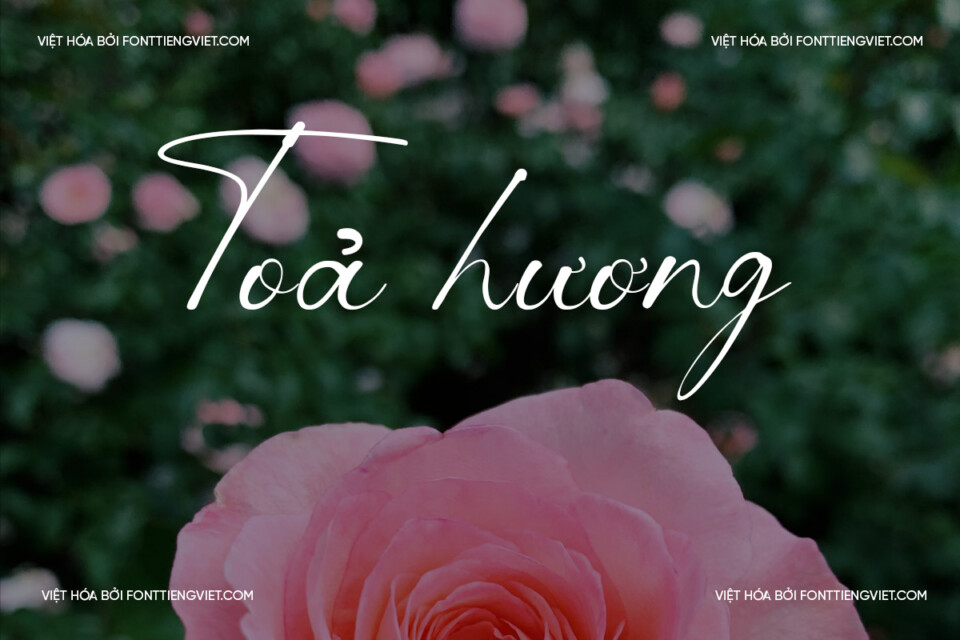
Trong thế giới thiết kế đồ họa đầy màu sắc và sáng tạo, việc lựa chọn một Font Chữ phù hợp có thể tạo nên sự khác biệt đáng kể cho bất kỳ dự án nào. Đặc biệt, với những ai đang tìm kiếm sự tinh tế, mềm mại và một chút cá tính nghệ thuật, Font Việt hóa 1FTV VIP Lorenna Script nổi lên như một lựa chọn không thể bỏ qua. Đây không chỉ là một font chữ đơn thuần, mà còn là một công cụ mạnh mẽ giúp truyền tải cảm xúc và câu chuyện thông qua từng nét chữ. Từ những thiệp mời sang trọng, poster quảng cáo độc đáo cho đến các ấn phẩm cá nhân, Lorenna Script Việt hóa mang đến một vẻ đẹp vượt thời gian, kết hợp hài hòa giữa nét cổ điển và hiện đại, chắc chắn sẽ làm hài lòng cả những nhà thiết kế khó tính nhất. Bài viết này sẽ đi sâu khám phá những đặc điểm nổi bật và lý do tại sao font chữ này lại được ưa chuộng đến vậy.
Sức Mạnh Của Font Việt hóa 1FTV VIP Lorenna Script Trong Mọi Thiết Kế
Font Việt hóa 1FTV VIP Lorenna Script không chỉ đơn thuần là một kiểu chữ đẹp mà còn là một biểu tượng của sự sang trọng và tinh tế. Với thiết kế lấy cảm hứng từ những nét chữ viết tay mềm mại, uyển chuyển, font này mang đến một cảm giác rất “thật” và cá nhân hóa. Mỗi ký tự đều được chăm chút tỉ mỉ, từ độ cong của nét chữ đến khoảng cách giữa các chữ cái, tất cả đều tạo nên một tổng thể hài hòa và dễ đọc. Điều này đặc biệt quan trọng trong các dự án đòi hỏi sự chú ý đến từng chi tiết nhỏ, như thiết kế logo, bao bì sản phẩm hay các ấn phẩm cao cấp. Khả năng tương thích tốt với nhiều ngôn ngữ, đặc biệt là tiếng Việt với các ký tự dấu chuẩn xác, là một điểm cộng lớn, giúp các nhà thiết kế Việt Nam có thể tự tin sử dụng mà không lo lắng về lỗi hiển thị. Lorenna Script Việt hóa không chỉ là một font, đó là một phong cách.
Điểm mạnh thực sự của Lorenna Script nằm ở tính linh hoạt của nó. Dù bạn đang thiết kế một tấm thiệp cưới lãng mạn, một banner quảng cáo sáng tạo hay thậm chí là một bìa sách nghệ thuật, font chữ này đều có thể phát huy tối đa vẻ đẹp của mình. Sự mềm mại nhưng không kém phần mạnh mẽ của nó giúp tạo ra một điểm nhấn thị giác ấn tượng, thu hút ánh nhìn của người xem ngay từ cái nhìn đầu tiên. Đối với các dự án yêu cầu sự độc đáo và khác biệt, việc sử dụng Lorenna Script Việt hóa sẽ giúp sản phẩm của bạn nổi bật hơn hẳn so với những thiết kế thông thường. Đây là một lựa chọn tuyệt vời để thể hiện sự chuyên nghiệp và gu thẩm mỹ tinh tế của người thiết kế.
Ưu Điểm Nổi Bật Của Font Script Việt Hóa
Khi nói đến font chữ script, khả năng Việt hóa là một yếu tố then chốt, và Font Việt hóa 1FTV VIP Lorenna Script đã làm rất tốt điều này. Việc sở hữu một bộ font được Việt hóa đầy đủ không chỉ đảm bảo rằng các ký tự có dấu của tiếng Việt sẽ hiển thị một cách chính xác và đẹp mắt, mà còn giúp duy trì tính thẩm mỹ tổng thể của thiết kế. Không còn những lỗi hiển thị khó chịu hay sự không nhất quán về kiểu dáng giữa các ký tự có dấu và không dấu. Điều này giúp tiết kiệm đáng kể thời gian chỉnh sửa và đảm bảo chất lượng cao nhất cho sản phẩm cuối cùng. Một font script được Việt hóa tốt như Lorenna Script là minh chứng cho sự quan tâm đến người dùng Việt, mang lại trải nghiệm sử dụng trọn vẹn và hiệu quả.
Bên cạnh đó, phong cách viết tay của Lorenna Script còn giúp tạo ra một cảm giác thân thiện và gần gũi. Trong bối cảnh truyền thông ngày càng trở nên cá nhân hóa, việc sử dụng các yếu tố mang tính thủ công, nghệ thuật như font script này sẽ giúp thương hiệu hoặc thông điệp của bạn dễ dàng kết nối với đối tượng mục tiêu hơn. Nó gợi lên sự ấm áp, chân thành và một chút hoài niệm, rất phù hợp cho các ngành nghề như làm bánh, thủ công mỹ nghệ, nhiếp ảnh, hoặc các sự kiện đặc biệt. Sự đa dạng trong ứng dụng làm cho font chữ này trở thành một tài sản quý giá trong bộ sưu tập của bất kỳ nhà thiết kế nào muốn tạo ra những tác phẩm có hồn và ý nghĩa.
Cách Tối Ưu Sử Dụng Lorenna Script Cho Dự Án Của Bạn
Để tối ưu hóa việc sử dụng Font Việt hóa 1FTV VIP Lorenna Script, có một vài mẹo nhỏ mà bạn có thể áp dụng. Đầu tiên, hãy sử dụng font này cho các tiêu đề, slogan, hoặc những đoạn văn bản ngắn cần tạo điểm nhấn mạnh mẽ. Do tính chất là một font script, việc dùng nó cho toàn bộ các đoạn văn bản dài có thể gây khó đọc. Thay vào đó, hãy kết hợp Lorenna Script với một font sans-serif hoặc serif đơn giản, dễ đọc cho phần nội dung chính. Sự tương phản giữa hai loại font sẽ tạo nên một bố cục cân bằng và chuyên nghiệp. Ví dụ, bạn có thể dùng Lorenna Script cho tên thương hiệu hoặc tiêu đề của thiệp mời, và dùng một font chữ cơ bản hơn cho các chi tiết thông tin.
Thứ hai, hãy chú ý đến màu sắc và kích thước. Lorenna Script sẽ tỏa sáng nhất khi được đặt trong một không gian đủ thoáng và có màu sắc tương phản tốt với nền. Đừng ngại thử nghiệm với các kích thước khác nhau để xem font chữ này thể hiện tốt nhất ở đâu. Đôi khi, một chút biến tấu về màu sắc hoặc hiệu ứng đổ bóng cũng có thể làm tăng thêm vẻ đẹp và sự độc đáo của font. Cuối cùng, luôn luôn kiểm tra tổng thể thiết kế trên các nền tảng và thiết bị khác nhau để đảm bảo rằng font hiển thị đẹp mắt và không bị lỗi. Lorenna Script không chỉ là một font chữ, mà là một yếu tố nghệ thuật đòi hỏi sự tinh tế trong cách sử dụng để phát huy hết giá trị.
Tóm lại, Font Việt hóa 1FTV VIP Lorenna Script là một lựa chọn tuyệt vời cho những ai đang tìm kiếm sự pha trộn giữa vẻ đẹp cổ điển và nét hiện đại trong thiết kế. Với khả năng Việt hóa hoàn chỉnh, phong cách viết tay tinh tế và tính ứng dụng cao, font chữ này chắc chắn sẽ làm phong phú thêm bộ sưu tập của bất kỳ nhà thiết kế đồ họa nào. Từ việc tạo ra những tác phẩm mang đậm dấu ấn cá nhân cho đến việc nâng tầm các dự án thương mại, Lorenna Script đều thể hiện xuất sắc vai trò của mình. Đừng ngần ngại khám phá và thử nghiệm với Font Chữ đặc biệt này để mang đến một hơi thở mới cho các ý tưởng sáng tạo của bạn. Hãy để Lorenna Script giúp bạn kể câu chuyện của mình một cách độc đáo và đầy cảm xúc.